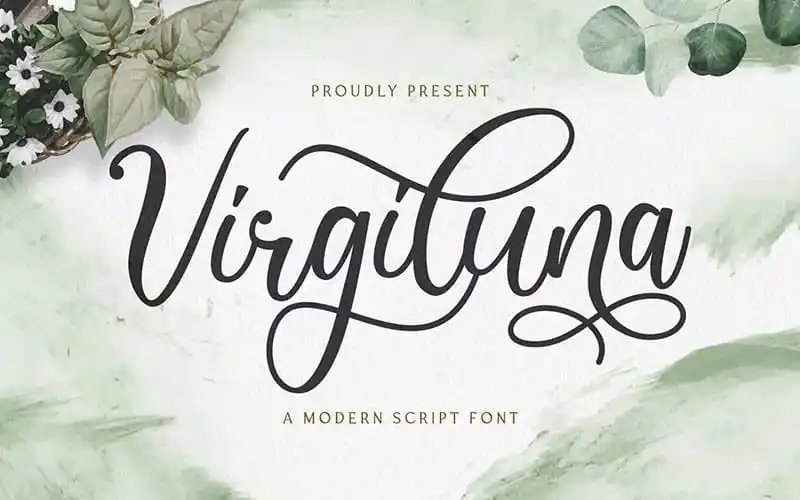
Virgiluna Calligraphy Font – Fonte Grátis
Virgiluna Calligraphy Font
A Virgiluna é uma fonte de script calligrafia com estilo de escrita moderna e autêntica. Criada usando um pen de canetinha, esta fonte é perfeita para uma variedade de usos, desde marcas de marca fashion até cartões de convite de casamento, cards de negócios, selos de marca, assinaturas e até mesmo gravações artísticas. Com seu estilo de escrita autêntica e moderno, a Virgiluna oferece um toque único para qualquer projeto de design onde você deseja incorporar uma pitada de elegância naquilo que está à mão. Seja na criação de cartões pessoais ou em uma campanha de marketing impactante, esta fonte é o instrumento perfeito para levar seu trabalho a um nível mais sofisticado. Não deixe de experimentá-la no próximo projeto onde você desejar incorporar alguns elementos de calligrafia.
Designer: Fancy Fonts